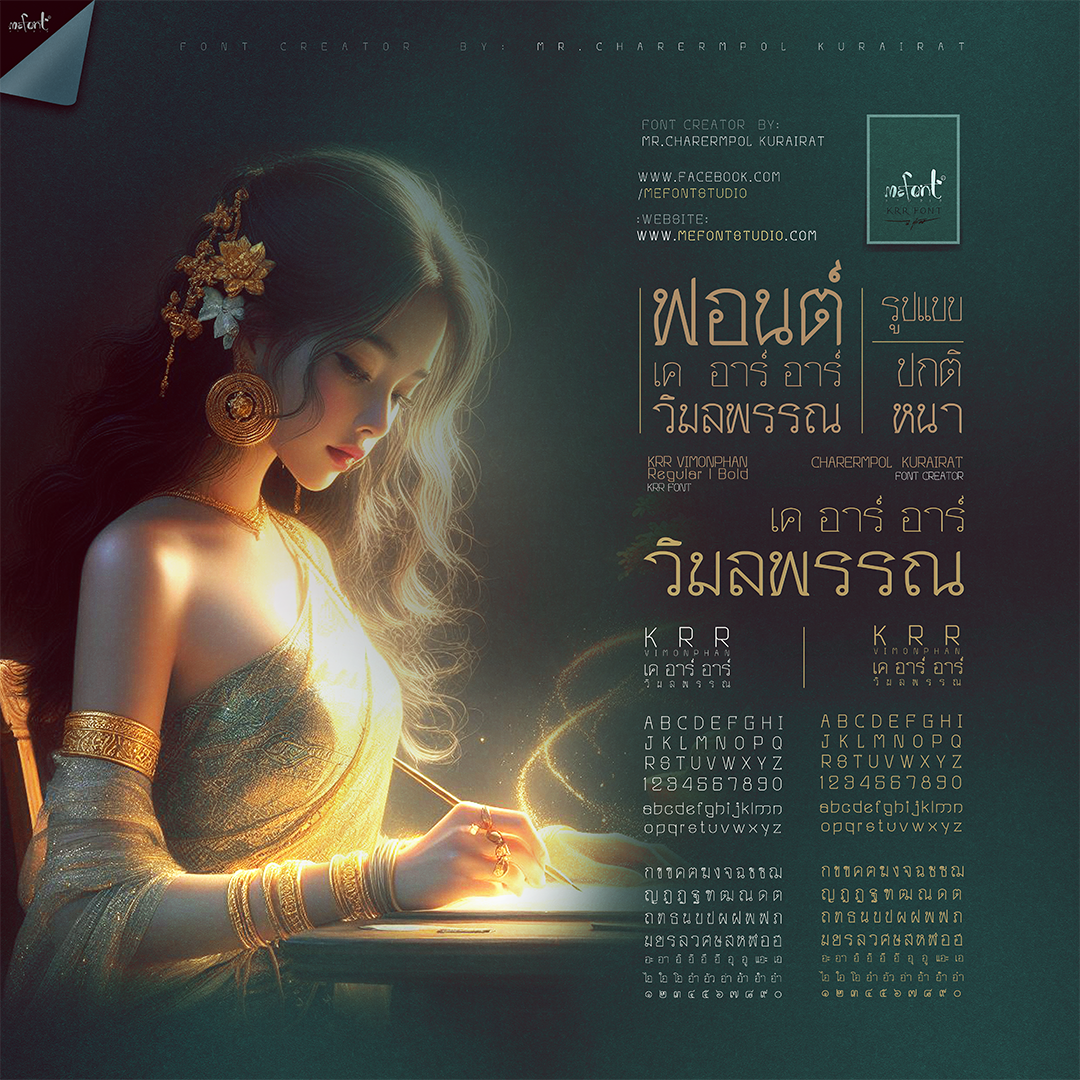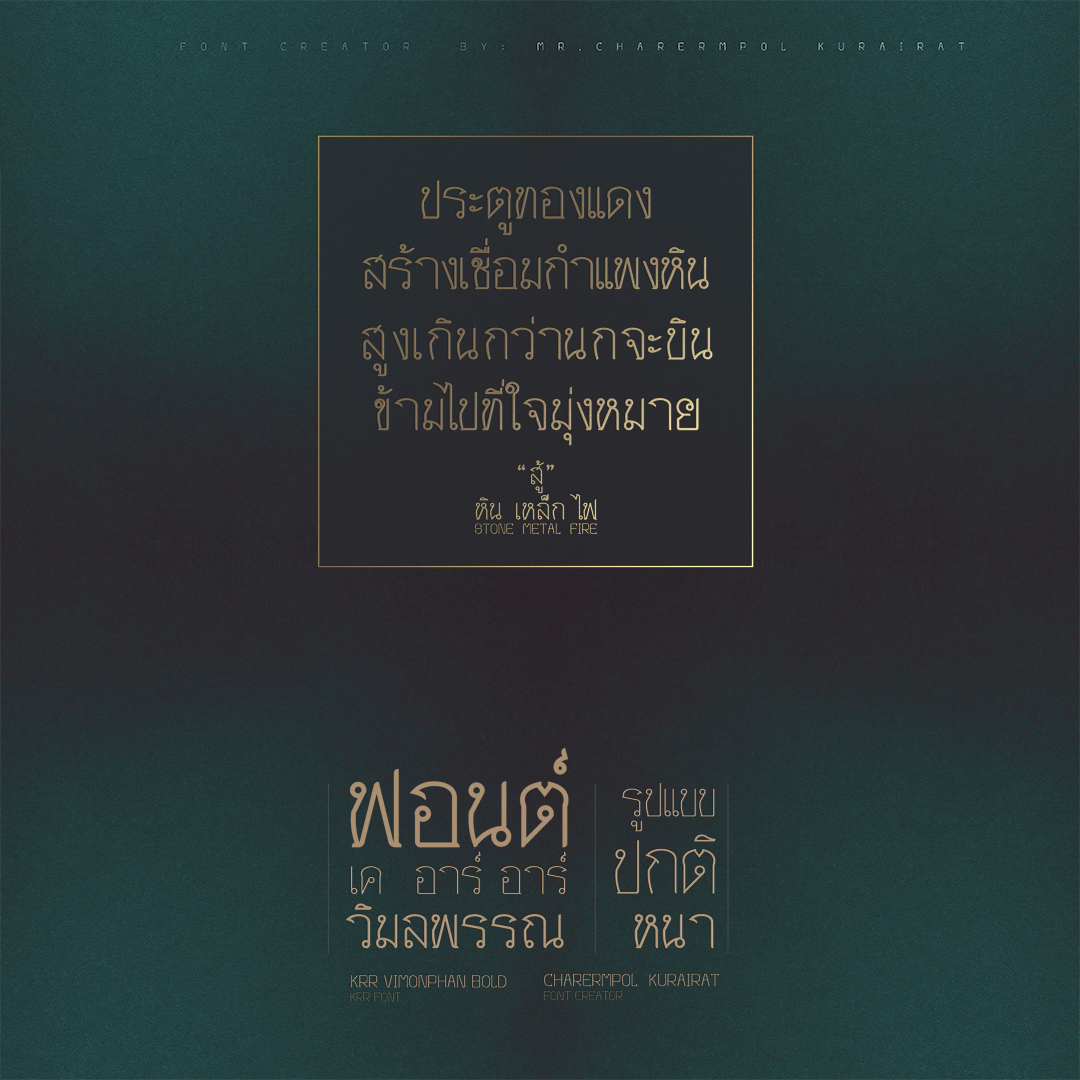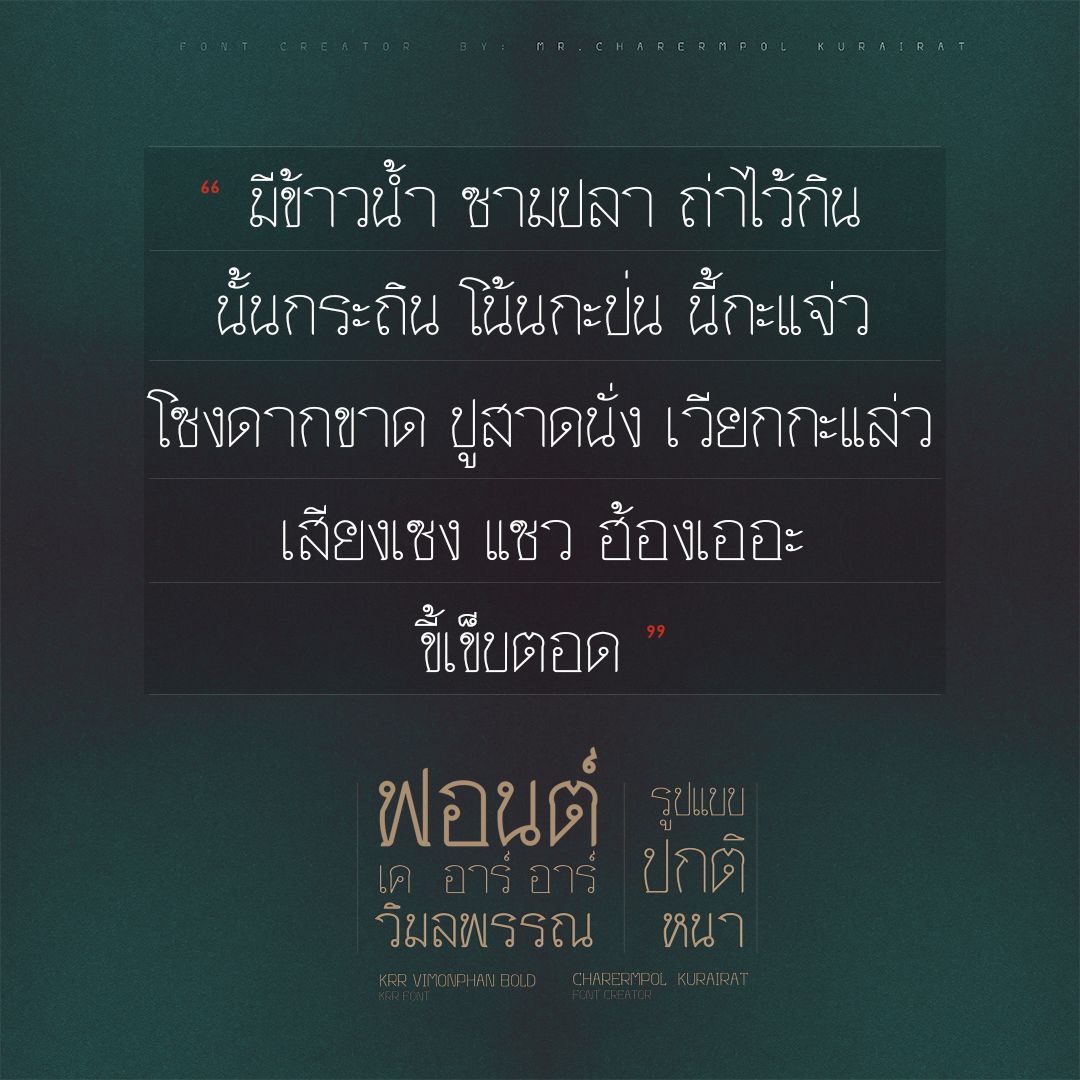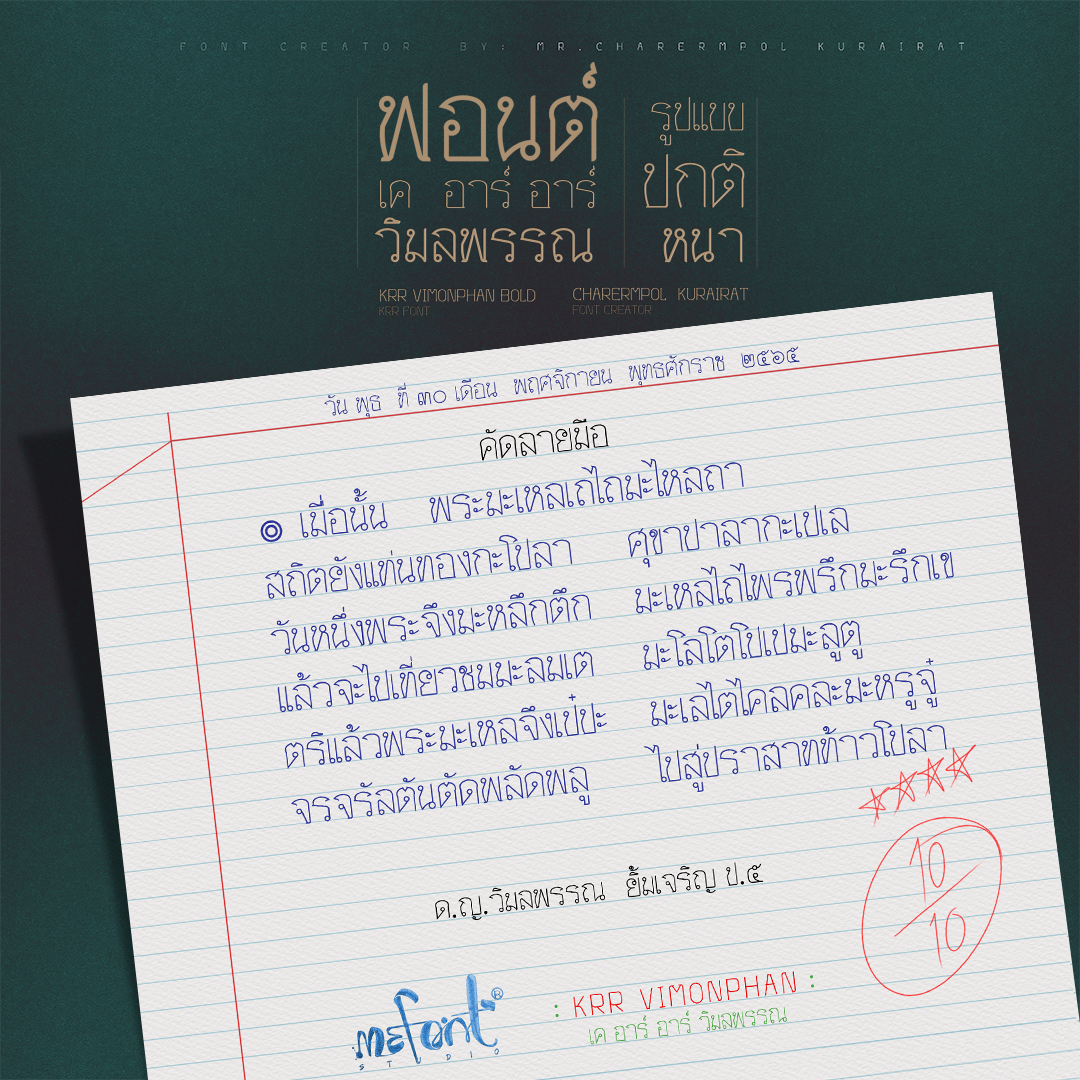
เคอาร์อาร์ วิมลพรรณ (KRR Vimonphan)
ความเพลิดเพลินเรื่องทำฟอนต์
อยากทำฟอนต์แบบนั้นแบบนี้ ตามอารมณ์ ฟอนต์วิมลพรรณ ก็เป็นอีกฟอนต์ที่อยากได้ฟิล คัดลายมือ
อิอิอิ บร๊ะ ออกมาได้สมใจนึกอยู่ครับ